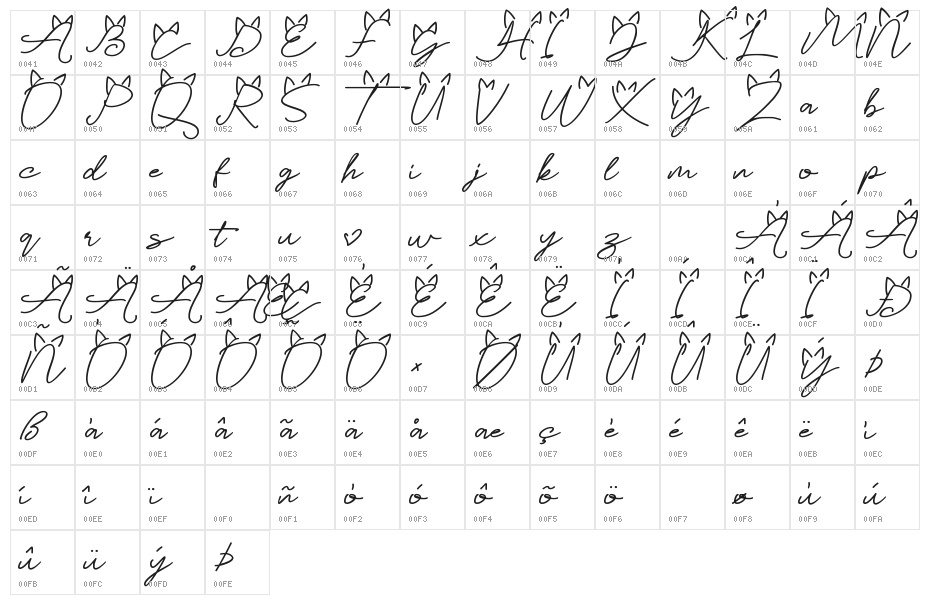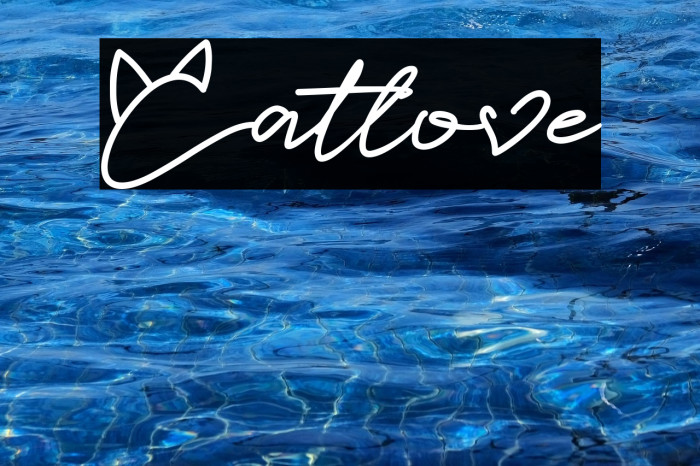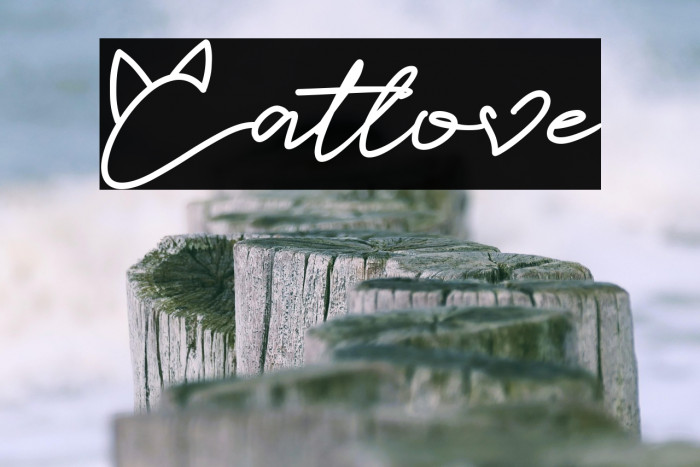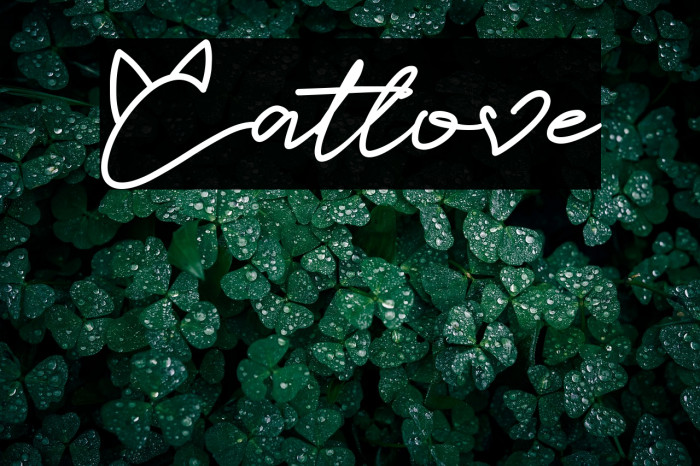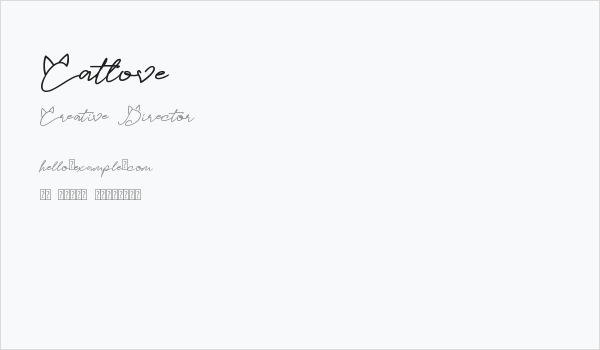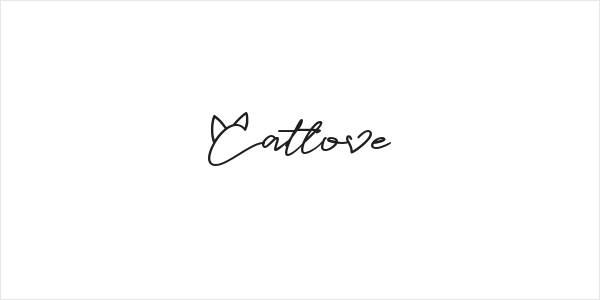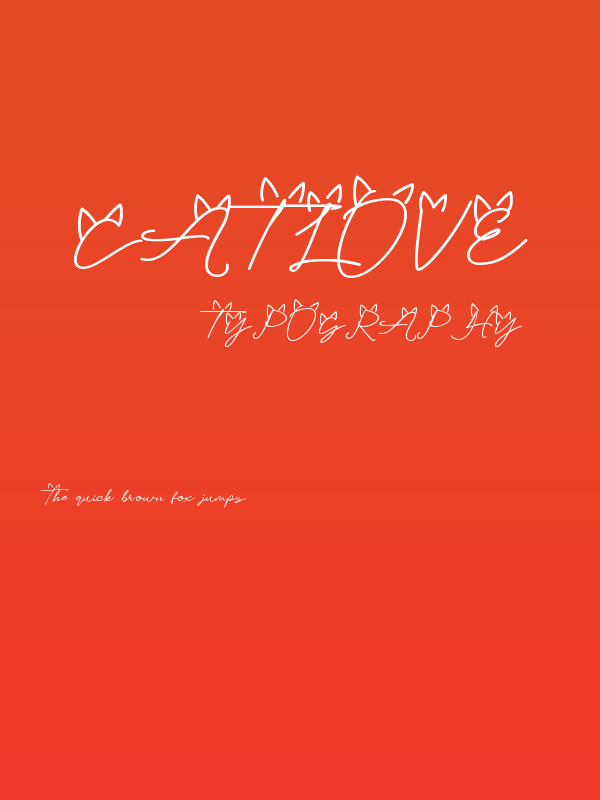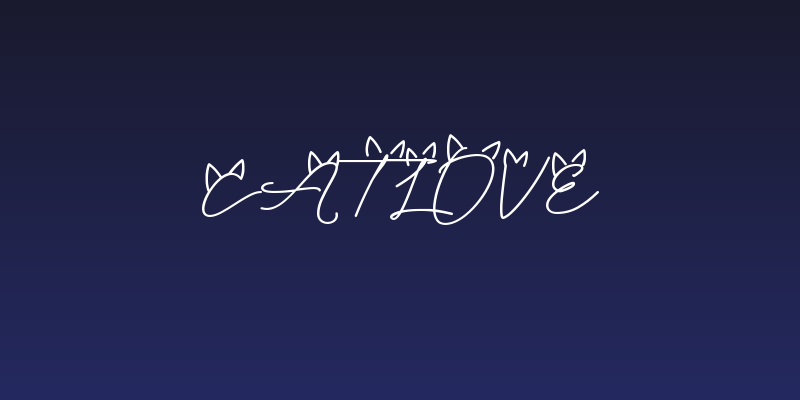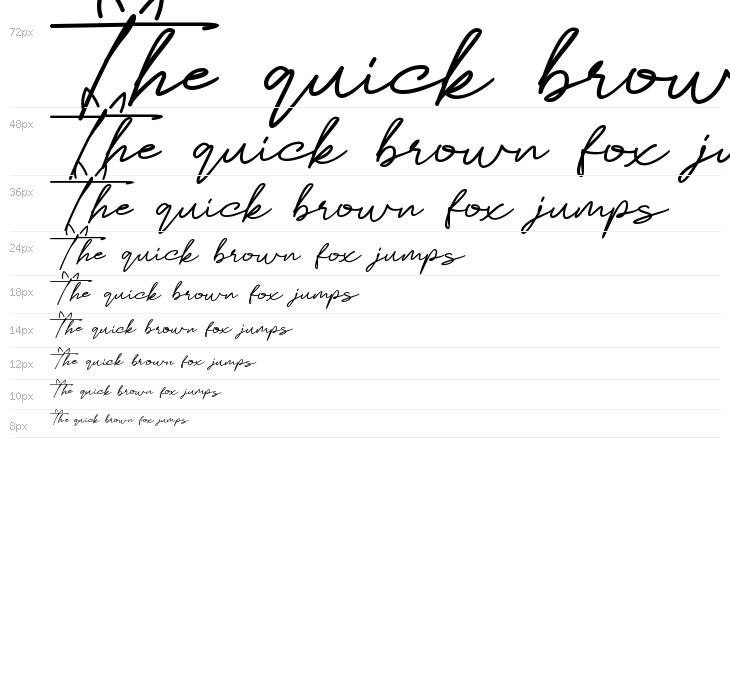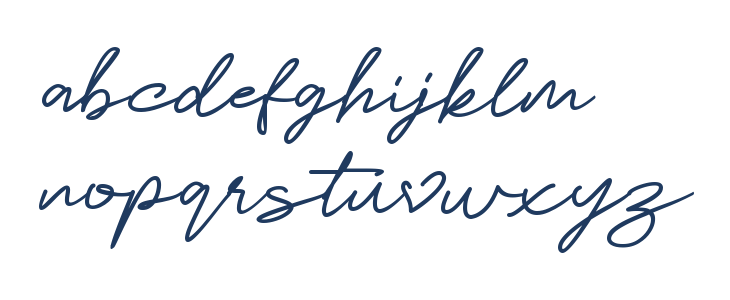
Catlove Font
| Gesamtstil | Playful, Whimsical |
| Anwendungsfall | Logos, Headlines, Invitations |
| Vorgeschlagene Projekte | Ideal for greeting cards, children's book covers, playful branding, and pet-related products. |